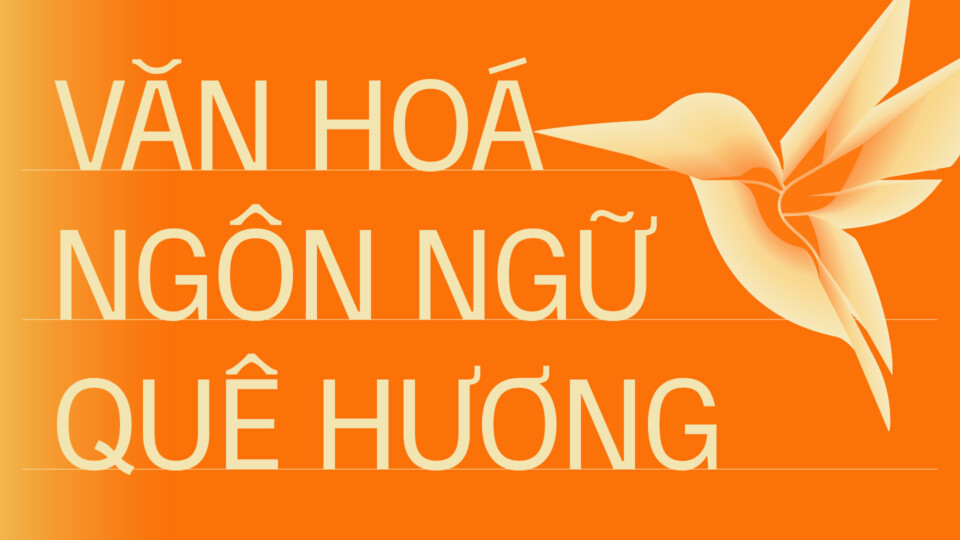
Font Tiếng Việt Young Lạc
Font Tiếng Việt Young Lạc – Bộ Font Chữ Tuyệt Vời Dành Cho Giáo DụcGiới thiệu về Font Tiếng Việt Young LạcTrong thiết kế đồ họa học đường, việc lựa chọn một Font Miễn Phí phù hợp đóng vai trò cực kỳ quan trọng. Font Tiếng Việt Young Lạc chính là giải pháp hoàn hảo mang lại làn gió mới cho các bài giảng và tài liệu học tập. Với thiết kế chỉn chu, bộ font này giúp mọi ý tưởng sáng tạo của thầy cô và học sinh trở nên sinh động hơn bao giờ thế.Ưu điểm nổi bật của Font Tiếng Việt Young LạcThiết kế gần gũi và tối ưu hiển thịBộ Font Tiếng Việt Young Lạc sở hữu các đường nét bo tròn mềm mại, tạo cảm giác thân thiện và dễ nhìn. Kiểu dáng này rất phù hợp với tâm lý học sinh, giúp các em tiếp thu kiến thức một cách tự nhiên mà không bị áp lực. Từng ký tự đều được chăm chút kỹ lưỡng, đảm bảo tính thẩm mỹ cao trên cả màn hình trình chiếu lẫn trang giấy in.Hỗ trợ tiếng Việt hoàn chỉnh và đa dụngĐiểm cộng lớn nhất của font chữ này là khả năng hiển thị trọn vẹn hệ thống dấu tiếng Việt mà không bị lỗi font hệ thống. Nhà trường có thể ứng dụng bảng mã này để thiết kế slide bài giảng PowerPoint, làm báo tường, chứng nhận khen thưởng hoặc trang trí bảng tin lớp học. Sự đồng bộ này giúp nâng cao tính chuyên nghiệp cho mọi hoạt động giáo dục.Cách ứng dụng font chữ hiệu quả trong học đườngĐể bài thiết kế đạt hiệu quả thị giác cao nhất, bạn nên kết hợp font chữ này với các tông màu tươi sáng như xanh dương, xanh lá hoặc màu vàng ấm áp. Hãy sử dụng font cho các tiêu đề lớn, khẩu hiệu hoặc tên bài học để tạo điểm nhấn thu hút sự chú ý của học sinh ngay từ cái nhìn đầu tiên.Kết luậnTóm lại, đây là công cụ đắc lực giúp nâng tầm không gian lớp học của bạn. Hãy tải ngay Font Miễn Phí, Font Việt Hóa, Font Tiếng Việt Young Lạc để sáng tạo nên những bài giảng trực quan, hấp dẫn và tràn đầy cảm hứng học tập mỗi ngày.